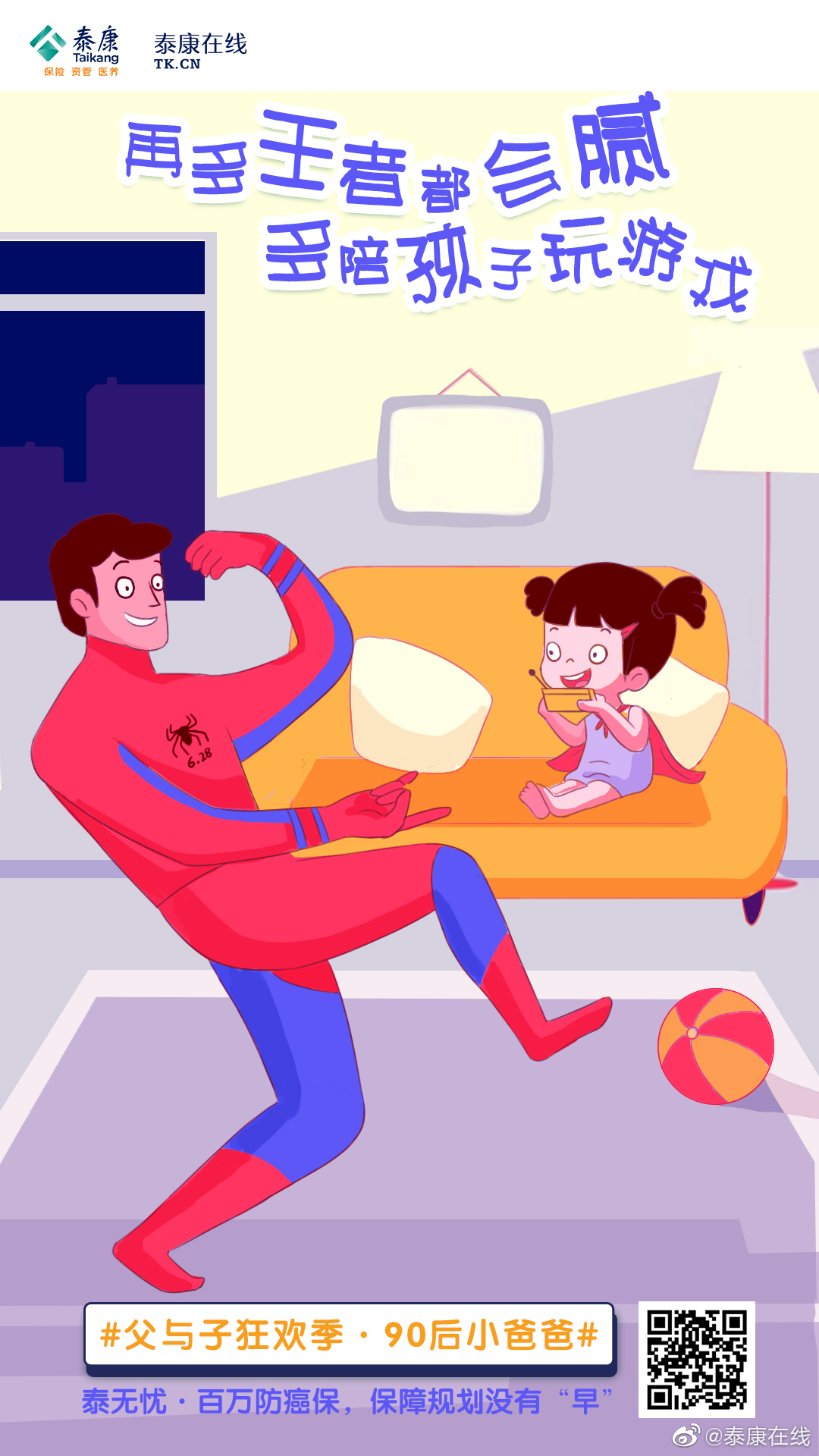
方正萌软体
孟萌
萌软体是萌艺体之后萌系字体的第二种,作者孟萌在字体创作时就一直在思考哪些会更能体现手绘字体的特色,于是想到了萌软体。萌软体是用硬笔来书写的仿软体字,字型既有软体的灵动,又有硬笔独特的“骨气”,是作者所书写的众多字体中,很喜欢的一款实用的字体。因为字型灵活,书写感强,所以特别适合广告创意创作使用。